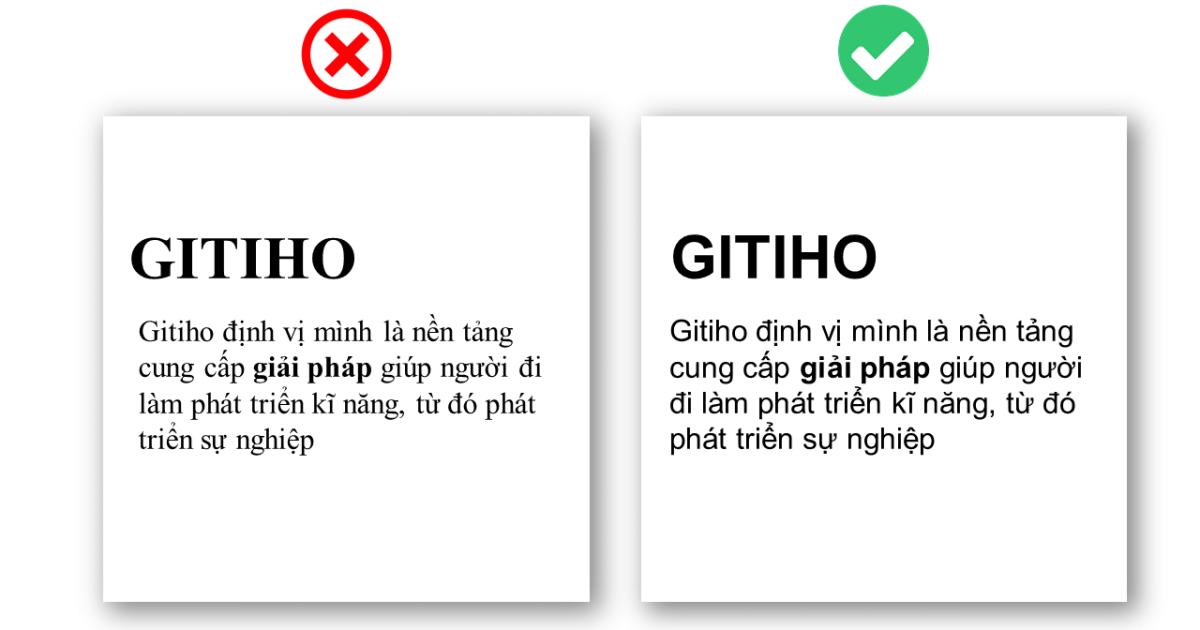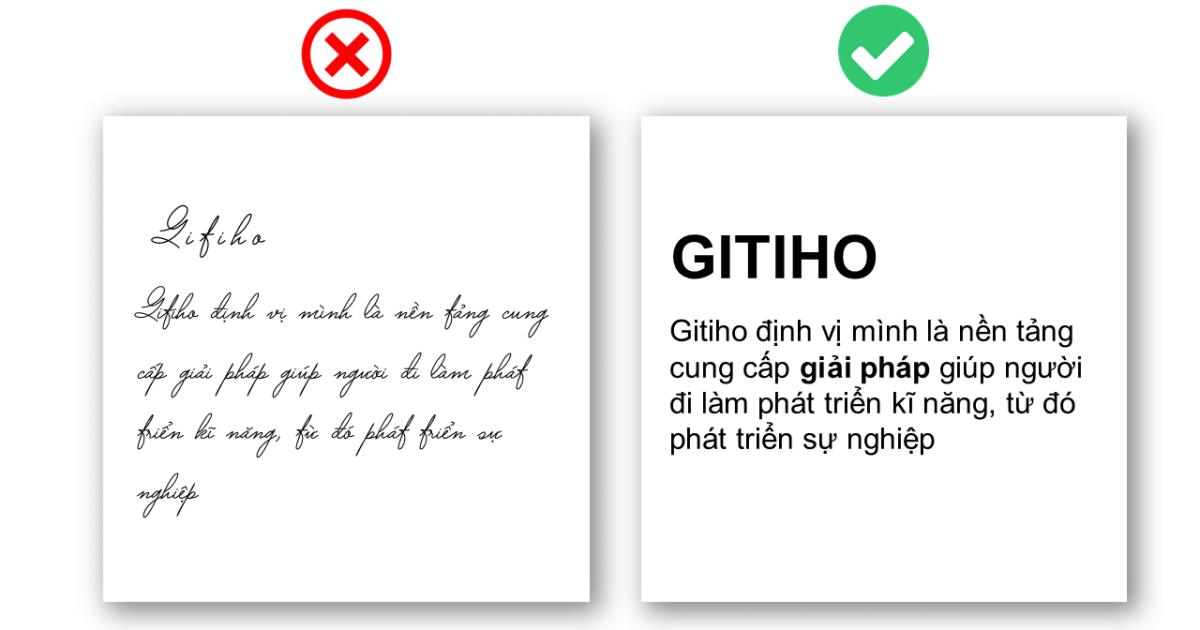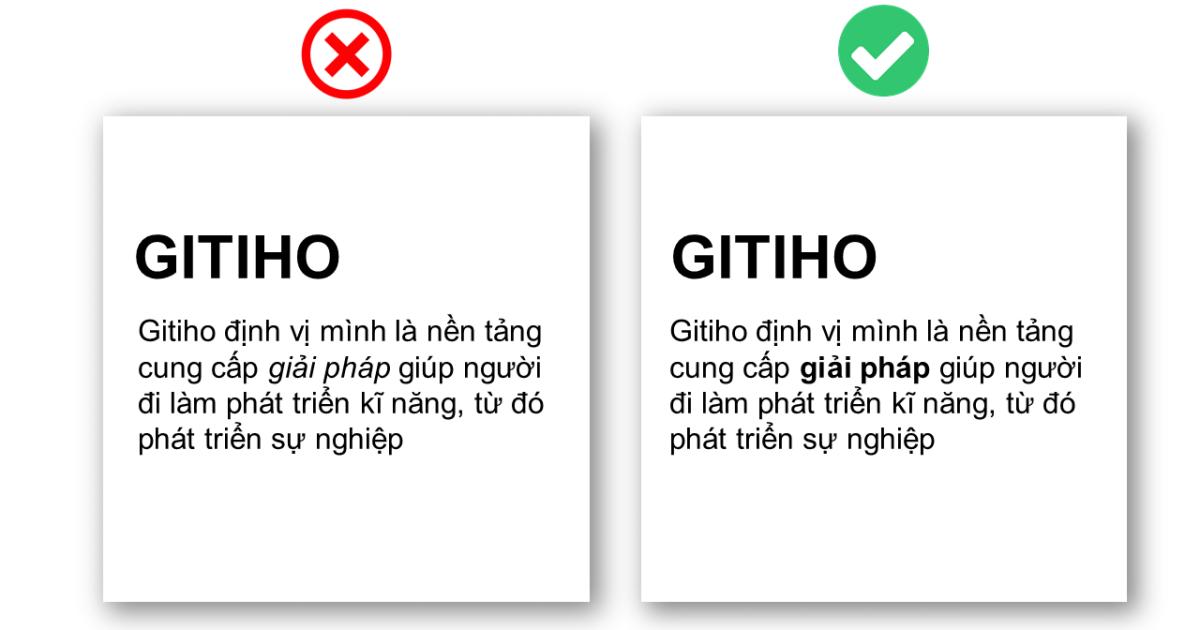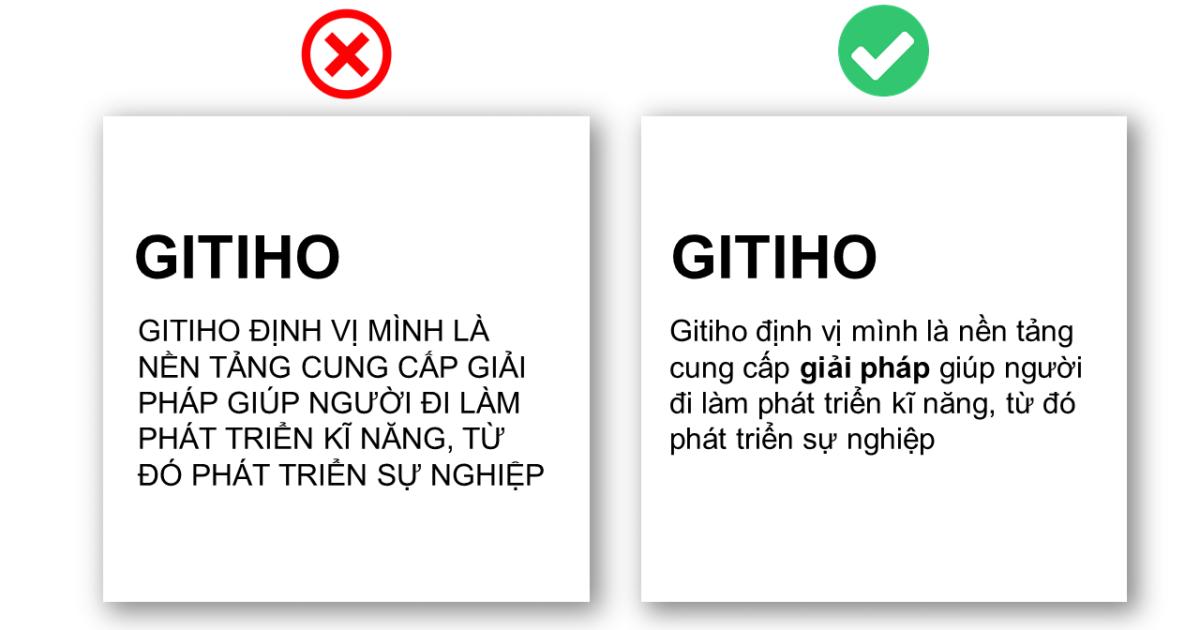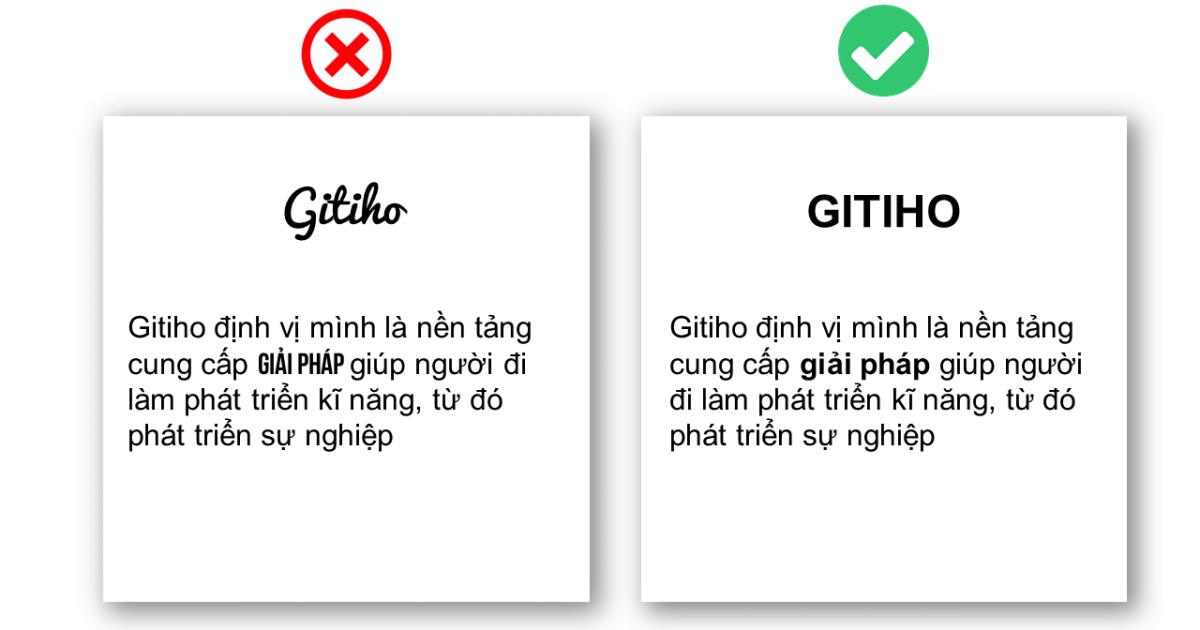
Không chỉ có hình ảnh, bố cục hay màu sắc, văn bản cũng góp một phần quan trọng trong việc tạo nên một slide đẹp, gây ấn tượng với người xem. Để văn bản đẹp, gây được ấn tượng và quan trọng là dễ theo dõi thì việc lựa chọn và sử dụng font chữ đúng cách là vô cùng cần thiết. Trong bài viết này, Gitiho sẽ chia sẻ với bạn các mẹo sử dụng font chữ chuyên nghiệp khi thiết kế slide trong PowerPoint.
Font chữ có chân (Serif) tuy tạo được cảm giác trang trọng, nghiêm túc và chuyên nghiệp, tuy nhiên, nếu sử dụng font chữ này cho các đoạn văn bản trong slide sẽ tạo nên cảm giác các chữ bị dính vào nhau, gây rối mắt cho slide và khiến người xem khó đọc, khó theo dõi. Vì vậy, nếu bạn muốn tạo sự nghiêm túc và trang trọng cho văn bản, bạn có thể sử dụng font chữ có chân cho tiêu đề lớn, còn với các đoạn văn bản trong slide, hãy dùng font chữ không chân như Arial, Monserrat nhé!
Font chữ viết tay sẽ làm cho slide của bạn thêm mềm mại và sáng tạo hơn, tuy nhiên, kiểu font chữ này lại khó đọc, khiến người xem khó theo dõi được theo slide và nội dung của bài thuyết trình. Hơn nữa, việc kết hợp font chữ viết tay với các font chữ khác khá là khó khăn và đòi hỏi phải có mắt thẩm mỹ tốt để kết hợp được đẹp nhất, tránh việc thiếu sự liên kết giữa các phần của slide. Vì vậy, nếu không thực sự cần thiết thì hãy tránh dùng font chữ này cho slide. Nếu muốn, bạn có thể sử dụng font chữ viết tay cho các slide chuyển tiếp, slide đề mục với kích cỡ chữ to và kết hợp với các hiệu ứng để thêm phần thú vị nhé!
Dù chúng ta muốn hay không cũng không thể ngăn tình trạng bị lỗi font chữ khi chuyển tệp PowerPoint từ máy tính của mình sang máy tính khác, vì máy tính khác không có bộ font chữ mà chúng ta đã sử dụng trong slide. Bạn có thể sử dụng chức năng Embed fonts để sao chép font chữ đi cùng với tệp, nhưng cách này có thể làm cho dung lượng của tệp bị tăng lên đáng kể. Vì vậy, để đảm bảo an toàn, bạn hãy sử dụng những font chữ phổ biến, cơ bản, mặc định có trong PowerPoint như Arial, Verdana, Tahoma..., vừa dễ đọc, dễ thiết kế lại tránh được tình trạng lỗi font chữ không đáng có.
Nếu muốn slide của mình nhìn chuyên nghiệp và đẹp mắt nhất thì hãy tránh sử dụng quá nhiều kiểu font chữ trong toàn bộ slide PowerPoint nhé. Chỉ nên sử dụng tối đa 2 hoặc 3 kiểu font chữ để đảm bảo tính nhất quán, đồng bộ cho toàn bộ slide trong PowerPoint.
Việc sử dụng chữ in hoa giúp cho phần văn bản bạn muốn nhấn mạnh được thể hiện rõ ràng và thu hút sự tập trung hơn. Tuy nhiên, nếu sử dụng chữ in hoa cho toàn bộ văn bản trong slide thì sẽ làm cho cả văn bản bị nặng nề và khó đọc, khó theo dõi. Vì vậy, nếu cần thiết, hãy chỉ sử dụng chữ in hoa cho các tiêu đề ngắn, các mục tiêu đề lớn nhất thôi bạn nhé!
Giống như các kiểu font chữ viết tay, chữ in nghiêng làm cho người xem khó đọc được văn bản và khó theo dõi bài thuyết trình. Vì vây, nếu muốn nhấn mạnh phần nào đó, hãy in đậm nó lên thay vì in nghiêng nhé!
Trình chiếu slide PowerPoint trên màn hình cho đồng thời rất nhiều người xem khác với đánh văn bản trên Word hay Excel, cần sử dụng chữ to, rõ ràng để mọi người có thể theo dõi, kể cả những người ngồi ở xa. Vì vậy, hãy sử dụng kích cỡ font chữ tốt nhất là tối thiểu 24pt, và đặc biệt không nên để kích cỡ font chữ nhỏ hơn 18pt.